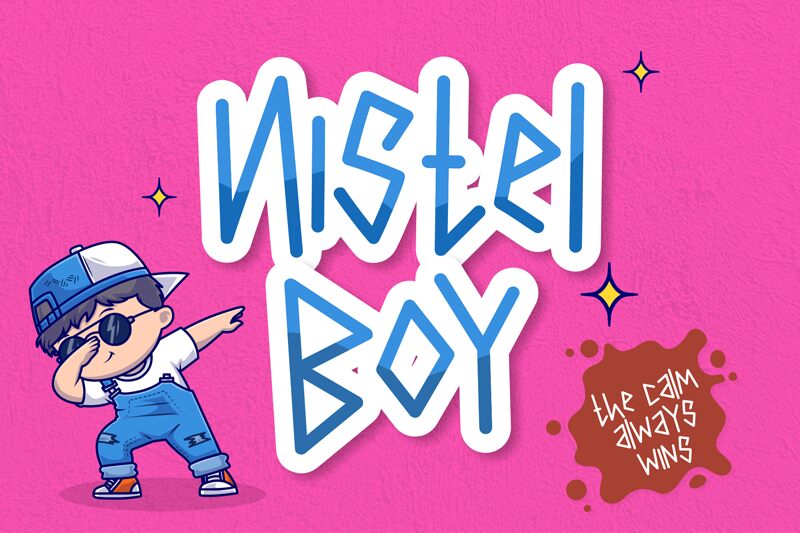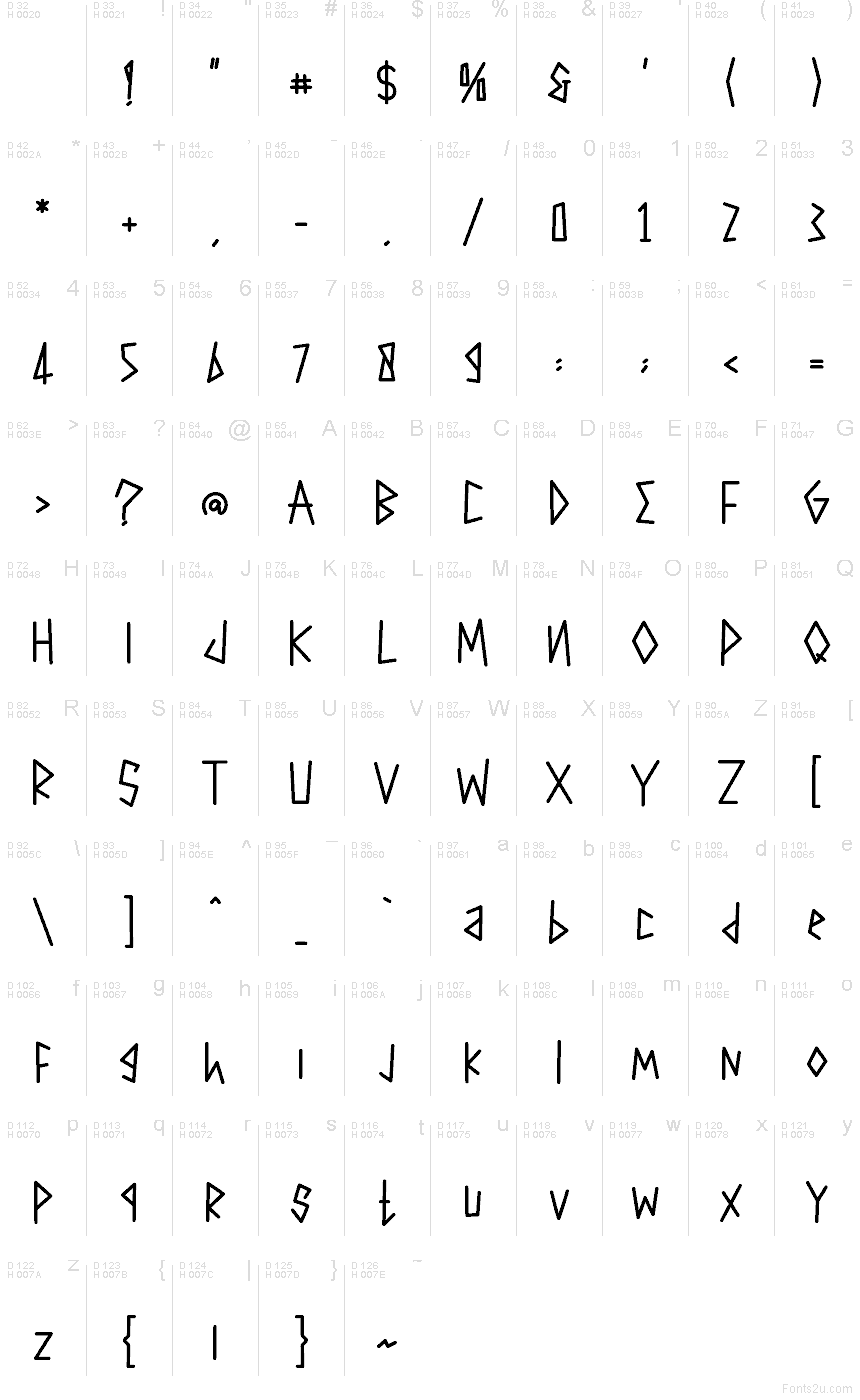
Nistel Boy od Mabhal Studio to darmowy krój pisma typu display w komiksowym stylu, charakteryzujący się surowym, odręcznym sznytem. Litery opierają się na nieregularnych pociągnięciach, ostrych kątach i luźnym rytmie przypominającym pisanie markerem, co nadaje im charakter gryzmołów na znaku lub szybkiej notatki, która stała się tytułem.
Idealnie pasuje do młodzieżowego brandingu, nagłówków plakatów, okładek zinów, grafik dla streamerów czy zabawnych opakowań, gdzie darmowy font ma sprawiać wrażenie swobodnego, a nie wygładzonego. Dzięki minimalistycznym i nieco niekonwencjonalnym formom, świetnie sprawdzi się również w kartach tytułowych i krótkich tekstach, które mają emanować niespokojną energią szkicownika.